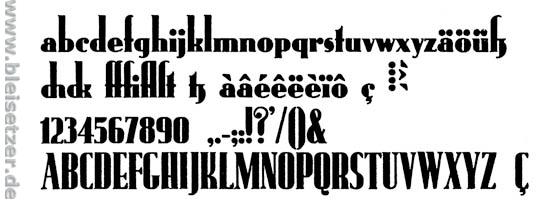
Font mit spitzen serifen
Welche Font ist das bzw. welche ist Ähnlich?
Leider nur ein sehr kleines Bild. Ich konnte noch keine vergleichbare Font finden.
Mist, ich war zu langsam! Dafür habe ich einen Font der noch näher dran ist, denke ich: Trara, die Egmont.